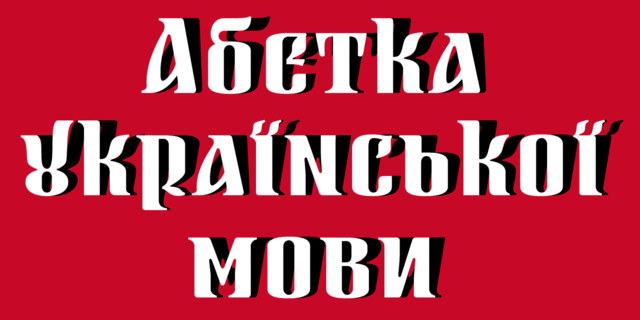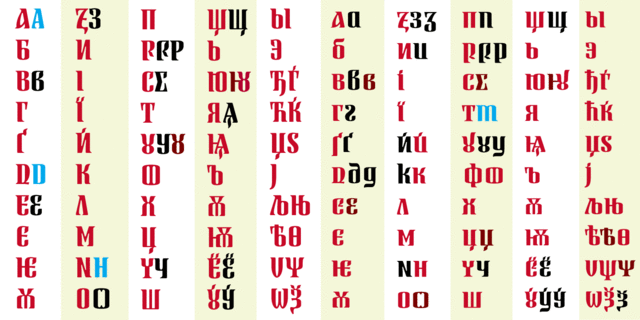
RUTA (Рута) – сверхжирное дополнение к популярной гарнитуре Rutenia (Рутенія) от Василия Чебаника. Шрифт содержит базовую латиницу и современную и старую славянскую кириллицу, ряд альтернатив и капитель одного размера со строчными, что позволяет стилистически вариативный набор – от старой кириллицы до современной болгарицы. Шрифт разработали Василий Чебаник, Виктор Харик и Геннадий Заречнюк при технической поддержке Андрея Шевченко и Константина Головченко в 2019 году.
Ассоциации c начертанием Ruta Ultra ItalicКачества и характер:
смелый, самобытный, характерный, оригинальный, этничный, натуральный, традиционный, старинный, гордый, колоритный, художественный, динамичный, пластичный, героический, живой, темпераментный, мотивирующий, активный, органический, племенной, высокий, гладкий, гибкий, вычурный, изысканный, пафосный, громкий, сильный
история, литература, театр, алкоголь, реконструкция, фольклор, музыка, летопись, тату, татуировка, сувенир, специи, геральдика, пиво, таверна, памятник, мемориал, паб, кино, водка, украшение, украшения, искусство, музей, трофей, награда, вышиванка, этнография, замок, банкнота, монета, туризм, легенда Стилистика: